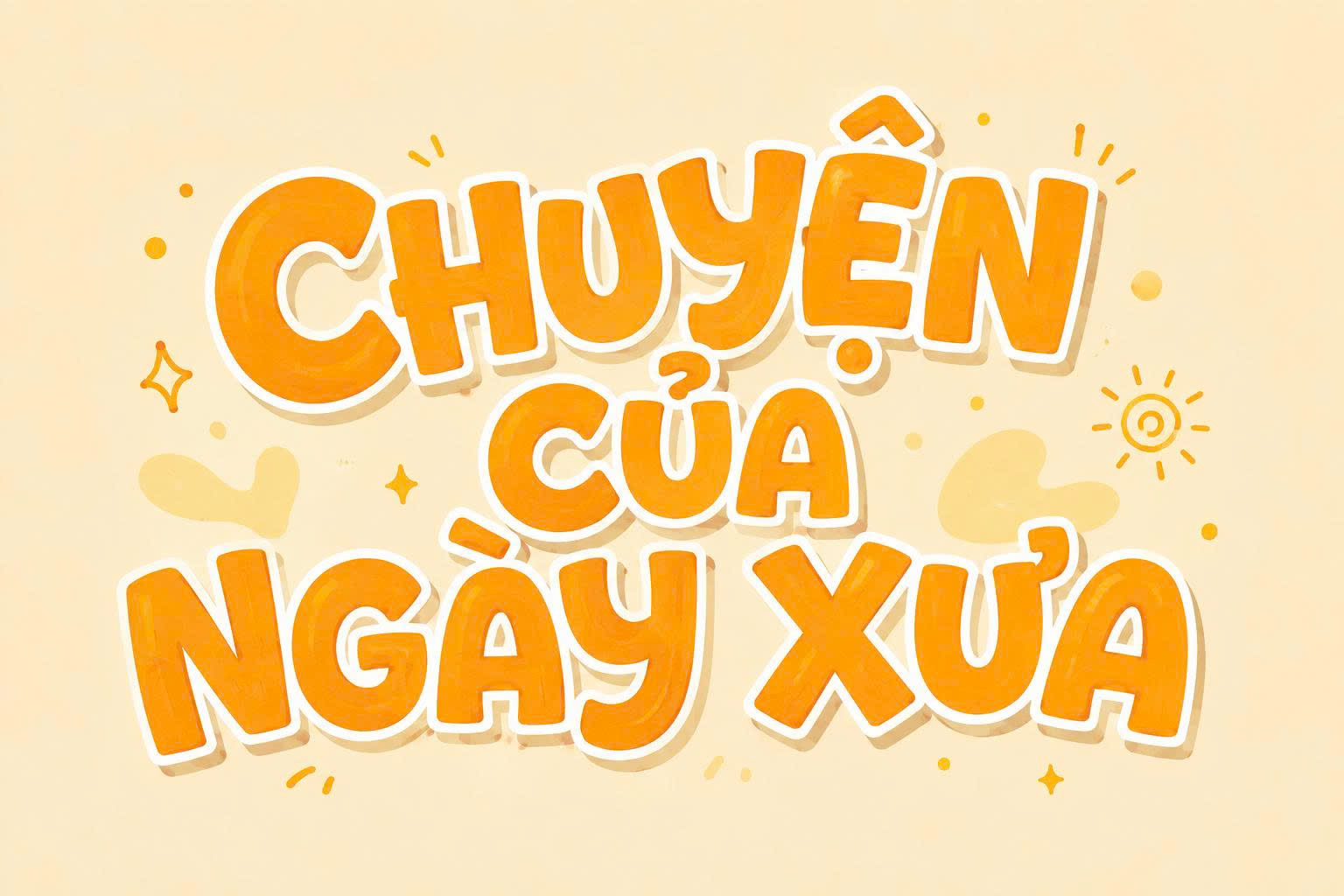
Font mùa hè Việt hóa là bộ sưu tập các phông chữ mang phong cách sôi động, rực rỡ và đầy năng lượng, lấy cảm hứng từ ánh nắng, biển xanh và các hoạt động dã ngoại đặc trưng của mùa nhiệt đới. Với những đường nét phóng khoáng, đôi khi là sự ngẫu hứng của nét cọ Brush hay sự mập mạp vui nhộn của dòng Display, bộ font này là lựa chọn số một cho các chiến dịch quảng cáo mùa hè. Doozypack.vn chia sẻ link tải font mùa hè miễn phí chuẩn, giúp bạn sở hữu những font chữ mùa hè tiếng Việt hoàn hảo để thiết kế bao bì, menu hay poster sự kiện mà không gặp bất kỳ lỗi hiển thị dấu thanh nào.
Đặc điểm của những bộ font chữ mùa hè đẹp
Một bộ font chữ mang hơi hướng mùa hè không chỉ đơn thuần là các ký tự, nó còn truyền tải cả một không gian tươi mát và đầy sức sống đến người xem.
Đường nét phóng khoáng, vui nhộn và đầy năng lượng
Đặc trưng lớn nhất của font chữ mùa hè đẹp là sự tự do trong cấu trúc. Bạn có thể dễ dàng bắt gặp các nét chữ viết tay không đồng đều, những đường cong uốn lượn như sóng biển hoặc các ký tự dày dặn, vững chãi gợi nhớ đến những tấm bảng hiệu tại các bãi biển nhiệt đới. Phong cách này giúp bản thiết kế thoát khỏi sự khô khan, mang lại cảm giác dễ chịu và sảng khoái cho khách hàng.
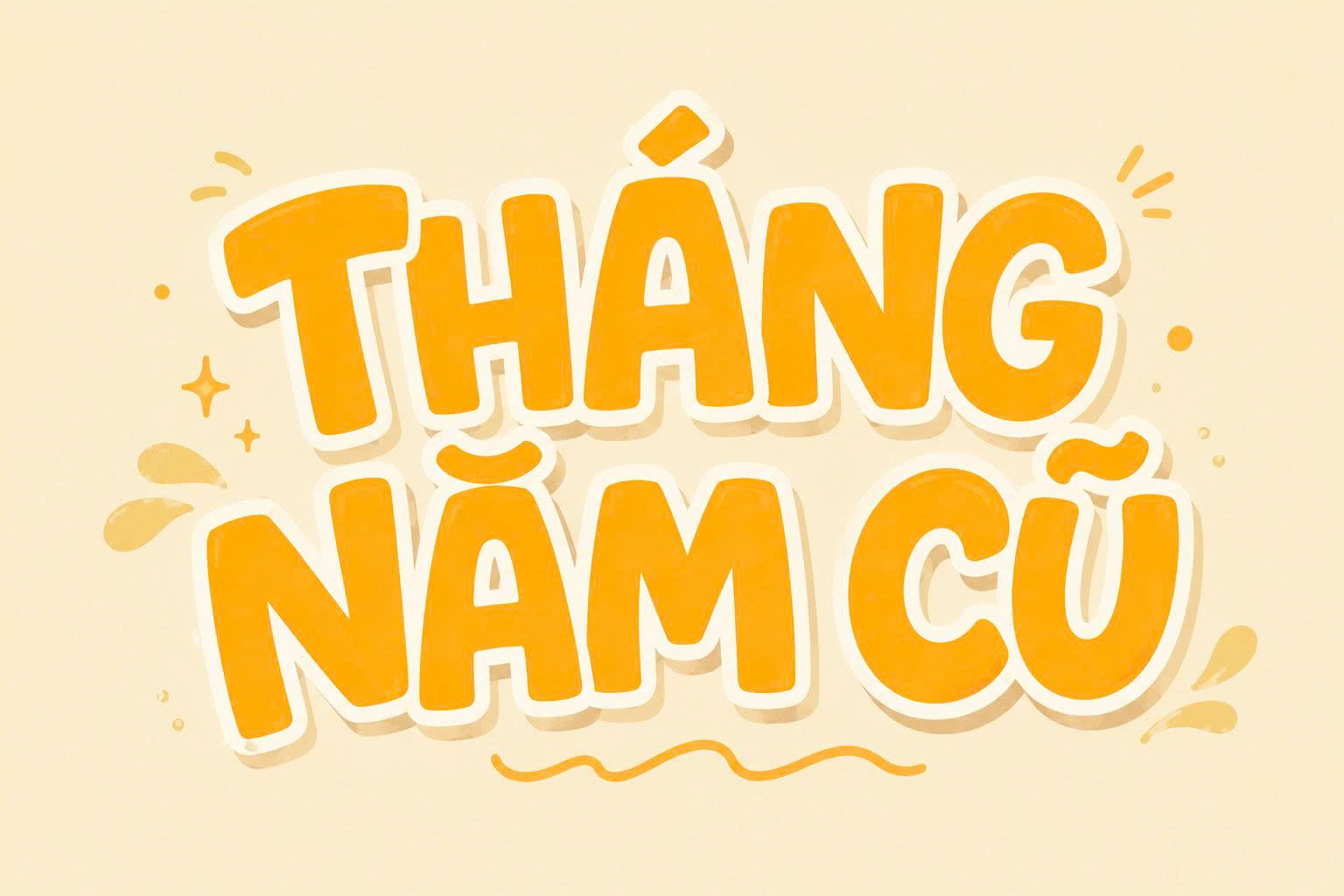
Màu sắc và cấu trúc chữ mang hơi thở của sự tự do
Các font chữ này thường đi kèm với các biến thể có độ dày lớn (Bold/Extra Bold) để dễ dàng kết hợp với những tông màu rực rỡ như vàng nắng, xanh cyan hay cam cháy. Cấu trúc chữ thường thoáng đãng, giúp các thông điệp quảng cáo trở nên nổi bật và dễ đọc ngay cả khi đặt trên nền hình ảnh phong cảnh phức tạp.
03 lý do nên tải font mùa hè Việt hóa cho các dự án thiết kế?
Trong ngành quảng cáo và in ấn tại Việt Nam, việc sử dụng các bộ font chuyên biệt cho mùa hè mang lại nhiều lợi ích thiết thực:
- Kích thích thị giác hiệu quả: Mùa hè là mùa của mua sắm và du lịch. Một bộ font chữ năng động giúp sản phẩm của bạn trông bắt mắt hơn trên kệ hàng.
- Hoàn thiện nội dung tiếng Việt: Sử dụng font chữ mùa hè tiếng Việt giúp bạn gõ các slogan như “Rực rỡ nắng hè” hay “Khuyến mãi cực đại” một cách trọn vẹn, không bị nhảy font ở các chữ có dấu đặc thù như ơ, ư, đ.
- Đa dạng hóa phong cách thiết kế: Từ phong cách Vintage Retro của thập niên 70 đến phong cách hiện đại tối giản, bộ sưu tập này đáp ứng mọi yêu cầu của designer.
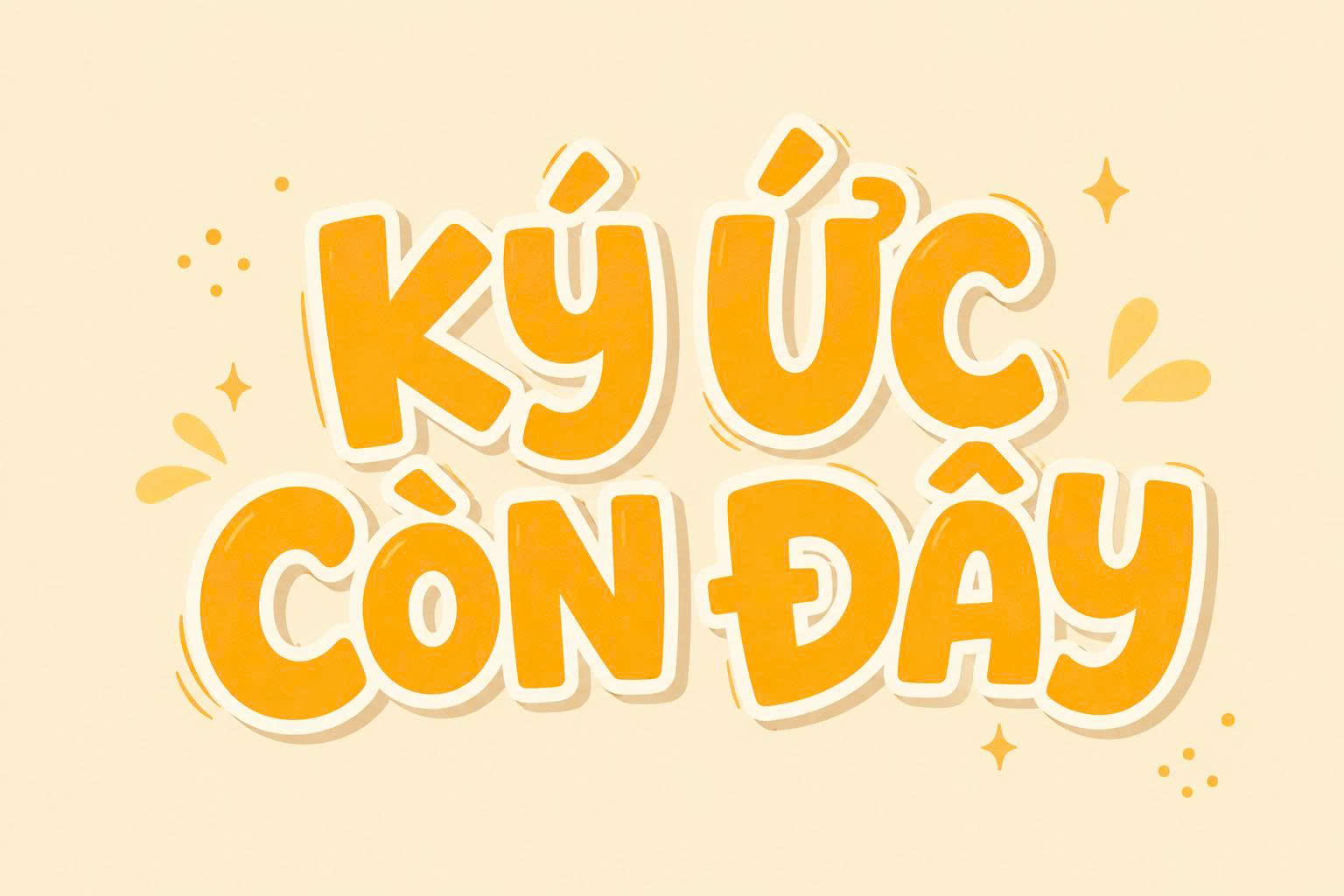
Ứng dụng của font chữ mùa hè tiếng Việt trong sản xuất bao bì
- Tem nhãn đồ uống & Kem: Các nét chữ Brush phóng khoáng cực kỳ phù hợp cho nhãn chai nước ép trái cây, trà trái cây nhiệt đới hay các hộp kem giải nhiệt.
- Bao bì thời trang hè: Túi giấy cho các shop đồ bơi, phụ kiện du lịch sử dụng font mùa hè giúp truyền tải đúng tinh thần năng động của bộ sưu tập.
- Ấn phẩm du lịch: Dùng làm tiêu đề cho các flyer, menu tại resort, khách sạn ven biển để tạo sự đồng nhất với không gian nghỉ dưỡng.